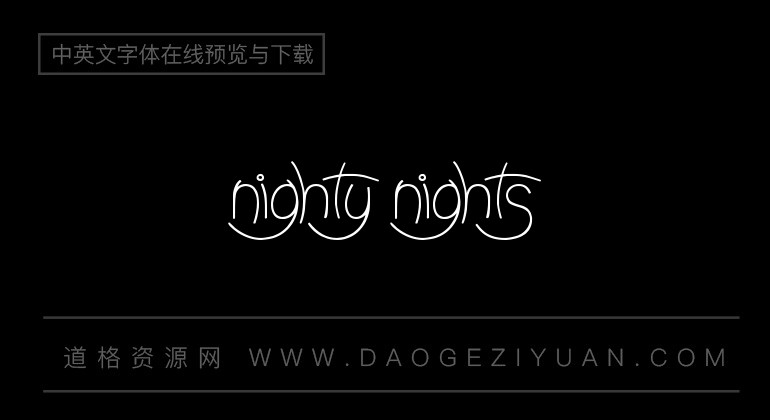
Nighty Nights
Nighty Nights 是一款由英国设计师Craig Ward设计的古典系列字体,它的外观灵感来自20世纪30年代的报刊,电影海报,和流行文化。Nighty Nights 字体具有独特的艺术性和细节,它可以让你的设计更加有趣,富有表现力。它的外观更具有时尚感,可以帮助你创造出有趣的品牌形象。
Nighty Nights是一款非常不错的手写艺术字体,具有很好的视觉感,适合于文化类的宣传设计、商业类品牌的广告和产品包装设计以及个性化文字排版等较多场景。
Nighty Nights字符映射图